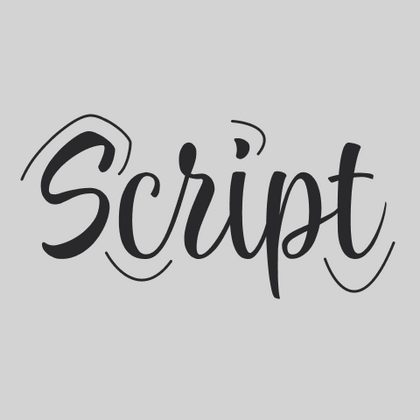
TT Nooks Script besitzt eine eigenständige Zeichnung, für die es kaum direkte Vergleichspunkte gibt.
Script-Schriften
Manchmal als Kursivschriften bezeichnet, imitieren diese Schriftarten menschliche Handschrift, ob geneigt oder aufrecht. Obwohl sie nur handgeschriebene Striche simulieren, schaffen sie elegante und ausdrucksstarke Designs. Skriptschriften verleihen einen Hauch von Handwerkskunst, Informalität und Wärme und sind ideal für Branding, Einladungen und dekorative Elemente. Die TypeType-Kollektion bietet eine vielfältige Auswahl an Schreibschriften, die auf unterschiedliche stilistische Bedürfnisse zugeschnitten sind.
TT Marks bietet eine Schreibschrift mit dynamischem Rhythmus, emotionalem Charakter und nostalgischem Flair, inspiriert von der klassischen amerikanischen Kunst der Schildermalerei. Dieses Handwerk, bei dem erfahrene Künstler Geschäftsschilder mit Pinseln und großer Präzision von Hand bemalten, erlebt heute eine wohlverdiente Renaissance in der Designwelt.
TT Disruptors ist eine flexible handgezeichnete Marker-Schrift. Ihr Design ist einzigartig: abgenutzte Kanten, variierende Strichstärken sowie verlängerte Ober- und Unterlängen verleihen ihr eine lebendige, dynamische Textur und handwerkliche Ausstrahlung. Der Charakter dieser Schrift ist temperamentvoll und emotional, zugleich aber warm und voller Seele.
TT Gentlemens ist eine dynamische handgeschriebene Schrift, die Ernsthaftigkeit und Präzision mit Eleganz und Raffinesse verbindet. Sie besitzt den Stil und Charakter eines echten Gentlemans: zurückhaltend und stets passend, zugleich aber selbstbewusst und markant.
Ohne falsche Bescheidenheit können wir sagen, dass TT Lovelies Script eines der komplexesten Projekte ist, die wir je umgesetzt haben: 1115 Glyphen, mehr als 2000 kontextuelle Alternativen, 10.000 Kerning-Paare und eine große Anzahl an OpenType-Features, darunter Ligaturen und Mediävalziffern.